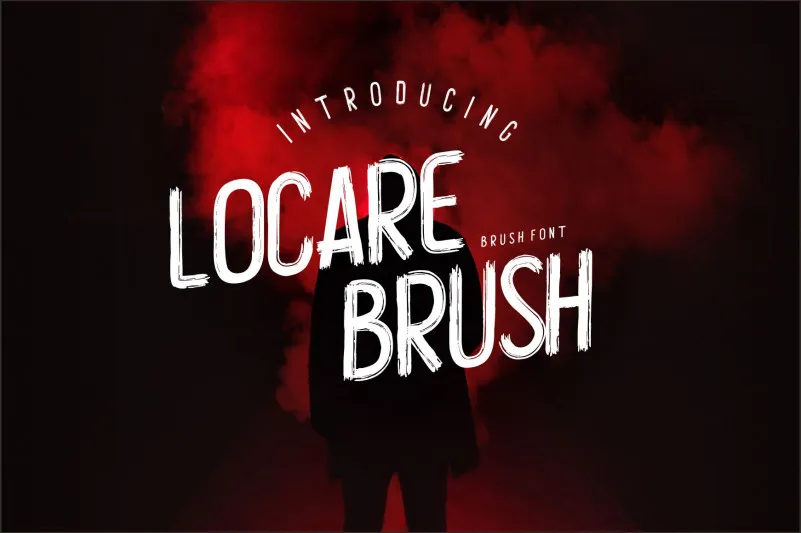
Locare Brush Font – Download Grátis
A Locare Brush Font é uma elegante seleção moderna de letra cursiva ideal para qualquer projeto visual criativo. Inspirada na arte da escrita com pincel, essa fonte se destaca por sua versatilidade e facilidade de uso. Seja você que esteja precisando de um logomarca, convites de aniversário, criação de texturas para fotos ou desenvolvimento de conteúdo para web – a Locare Brush Font está aqui para ajudá-lo a alcançar o próximo nível em sua criação. Com seu design fluido e moderno, você pode criar um lema único ou simplesmente decorar qualquer texto para adicionar profundidade e personalização. Adquira a Locare Brush Font agora e experimente suas incríveis capacidades de escrita com pincel!
Designer: miftah locare